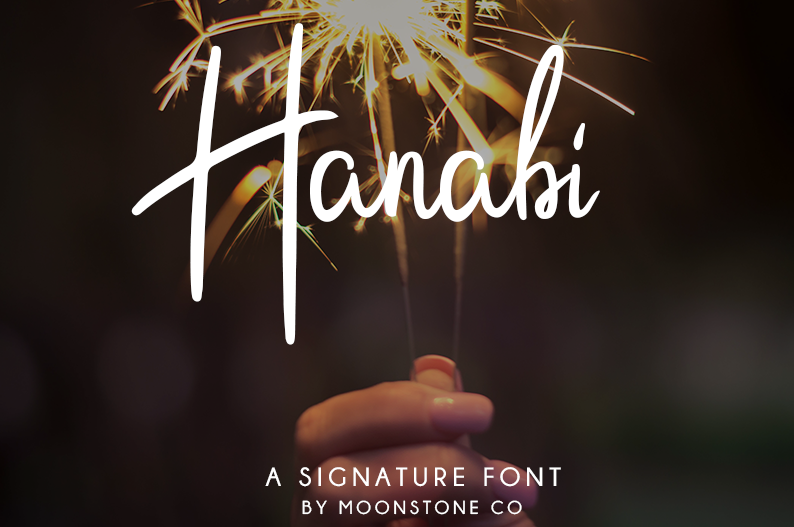
Hanabi Script Font – Download Grátis
Introduzimos a Hanabi Signature Font para seus projetos de design. Esta tipografia é uma obra puramente escrita à mão, com características únicas e autênticas. É perfeita para uso em convites, assinaturas, blogs, mídias sociais, cards de negócio e marcas de produtos. Suas linhas suaves e o tom delicado da Hanabi se destacam na comunicação visual do seu trabalho. Seja você um designer criativo ou um especialista em design gráfico, a Hanabi Signature oferece a oportunidade perfeita para capturar atenção com sua escrita única e original. Esse é mais que uma fonte; é um complemento de expressão e identificação visível.